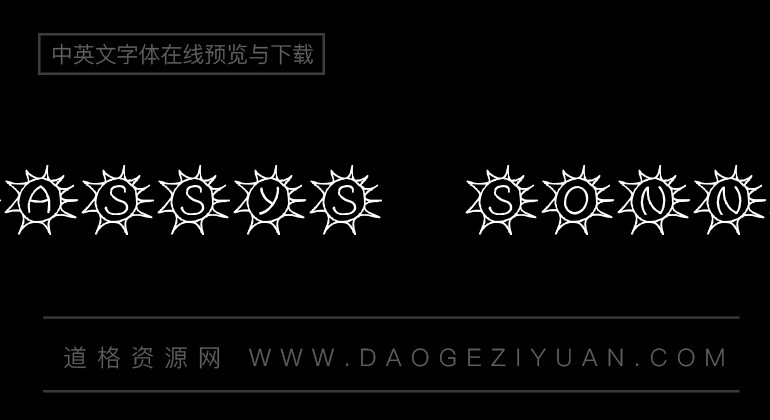
Sassys Sonne
? Sassys Sonne字体是一款简约、现代化的英文字体,它具有鲜明的曲线和清晰的细节,可以帮助您创建出精致的文字设计。它具有丰富的字体风格,可以满足您的各种设计需求,包括商业、网页、平面设计等。此外,它还提供了多种字重,可以帮助您更好地表达自己的想法。
Sassys Sonne是一款非常不错的手写艺术字体,具有很好的视觉感,适合于文化类的宣传设计、商业类品牌的广告和产品包装设计以及个性化文字排版等较多场景。
Sassys Sonne字符映射图